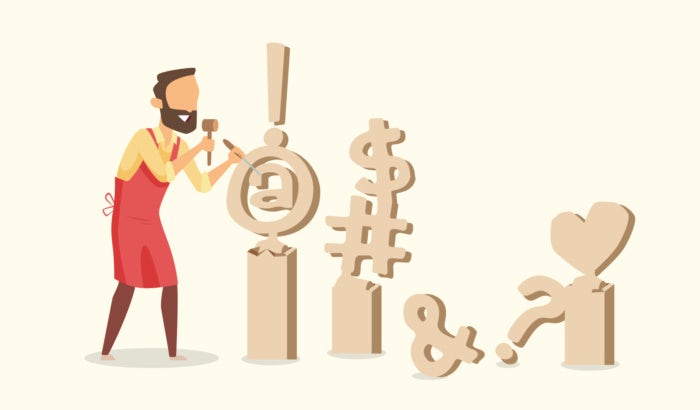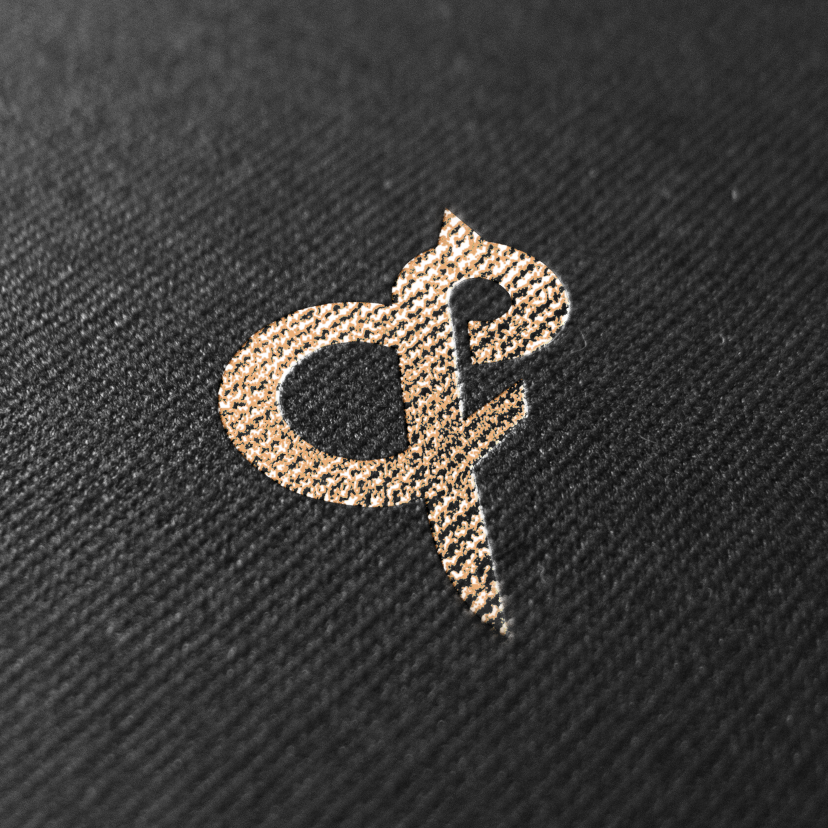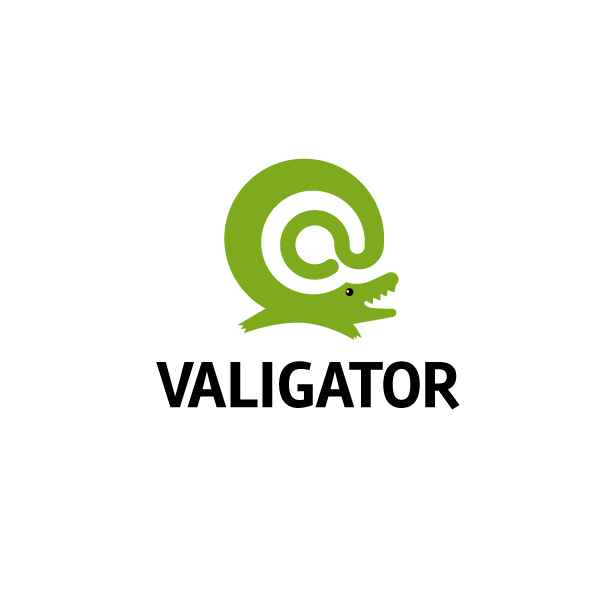
这7个符号你每天都用,但不一定知道它们的起源~
我们每天使用数千个符号。当我们找不到描述我们感受的词语时,我们用它们来传达信息和表达情感。
在设计领域,符号是图形元素的组合,可用于表示品牌的身份,传达其故事并影响消费者的感知方式。
但是,有没有想过每天看到的图形符号背后的起源?
在本文中,我们将探讨七个最广泛使用的图形符号的历史。了解符号的真正含义可以帮助您在自己的工作或公司的品牌中更具战略性地使用它。
1.&符号
设计师们总是无法满获得足够的&符号(&)。
对于设计师来说,这个符号是冒险的邀请,是表达创造力和四处玩耍的机会。Tobias Frere-Jones在一篇关于快速公司的文章中指出了这一点:
"&是一种恐龙。它本该在很久以前就灭绝了,但还是存活了下来。从视觉上看,它是孤独的……通常,通过设置先例和提供上下文,字母有助于形成彼此,但是这些字母并没有得到任何支持。“这使得画图变得困难,但同时也为实验和风险打开了一个异常大的窗口。”
由古罗马人创造的安培人首次出现在庞贝伊的墙上。它一开始是拉丁词et的表示,意思是“和”。
当孩子们说英文字母时,他们在字母本身可以作为一个词来使用(比如a和i)之前加上了本身---一个拉丁短语,意译为“本身”。这看起来像是“一个本身”,“i本身”等等。
最终,符号会出现在字母表的末尾。所以他们发音为“……x,y,z,和本身”,为了发音更快而变形为“……x,y,z,Amperand”。
由nnorth创作的Oats&Ivy徽标中带有创意设计的&符号
2.@符号
早在1971年,美国计算机程序员Ray Tomlinson(称为电子邮件的发明者)发送了第一封电子邮件,用无处不在的符号(@)表示收件人的位置。
今天,会计和编程专家最常使用at符号,但创意设计师就在他们后面。
@符号的起源有三个主要理论:
3.它是“each at”的缩写,首次记载于1536年的西班牙。佛罗伦萨商人Francesco Lapi将塞维利亚的一封信寄给罗马,用@符号表示一个单位的葡萄酒。“在那里,一杯三十分之一的葡萄酒,价值70或80个硬币,” 他写道,用@代表双耳瓶。
由于其独特的形状,@有许多昵称:
Strudel(以色列),猴子尾巴(丹麦),小鸭子(希腊),狗(俄罗斯),蜗牛(意大利),睡猫(芬兰),蠕虫(匈牙利),腌鲱鱼(捷克共和国),老鼠(中国) 等。
据意大利人说,这就是at符号变成蜗牛的方式。通过Jesper Aggergaard。
3.美元符号
您可能听说过美元符号($)是由字母“U”和“S”的字母组成的,就像“美国”一样。
其实不是这样的。
$符号来自“peso” 又名 “ps” 的缩写,最初发生在1770年代,当时英美人与西班牙人有贸易关系。“美元”这个名字来自旧波希米亚货币 - 塔勒。
在设计中,美元符号可以代表国家身份。
4.感叹号
感叹号(!)来自拉丁语“io”,意思是“欢呼”,这是表达喜悦和奇迹的经典方式。为了在纸上分享强烈的情感并节省写作时间,字母“i”写在“o”之上。
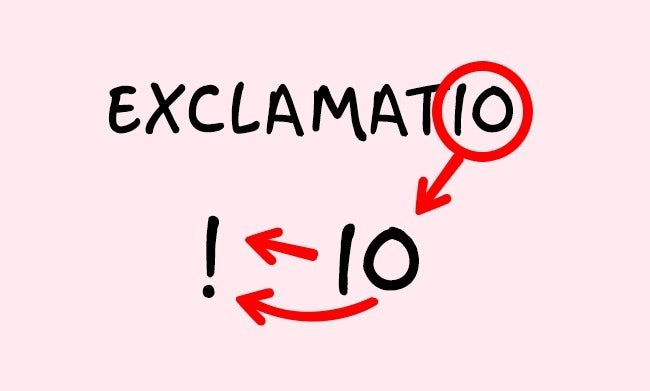
这就是感叹号的来源。通过Letssbuzz。
许多设计师发现这些符号具有多样性。广告牌,平面广告,商业广告,电影海报和网站中都可以见到它的身影。甚至谷歌在1999年的徽标中也有一个惊叹号!
5.#符号
“#”的起源与军队成员每三年服务收到的条纹相关联。它们被称为“hash标记”,可以在军用夹克上找到。
在20世纪80年代,#符号开始被称为“hash”,2007年,前谷歌开发人员Chris Messina使用Twitter建议人们开始使用#topic在同一主题上对推文或其他社交媒体帖子进行分组。在公众抱怨之后,这个符号开始被广泛使用起来。
然后就像电话键盘上的“pound”一样。在这里,拉丁语再次成为事物的根源。Pound是拉丁语中“libra pondo” 又名 “磅重” 的缩写。在写作时,当字母“l”和“p”交叉时,它可以提醒#符号之一。
什么是“octothorpe”?这一次,词源可以追溯到14世纪的“古挪威语”。在古挪威语中,“thorpe”翻译为“field”或“farm”。添加“octo”或“eight”,你就有“eight fields”或“octothorpe”。
今天,标签被广泛用于视频,对话,社交运动和设计中。
Artmin的黑客大会的Cult / Hacker标志
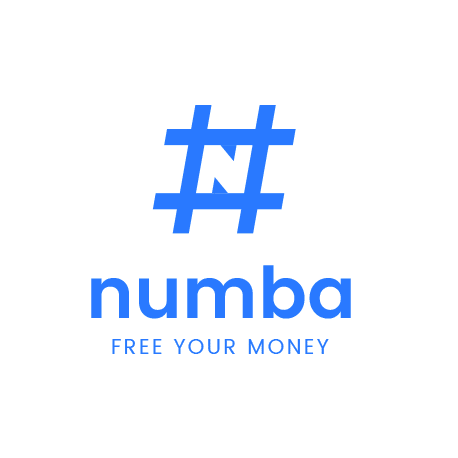
Teo Decu的聊天和汇款应用智能符号
6.无穷大符号
1655年,英国数学家约翰·沃利斯首次提出,无穷大符号被广泛用于物理学,计算机科学和代数中,通常代表潜在的无穷大,而不是实际上无限的数量。
但是如果你深入挖掘一下,你会发现这个符号具有古老的根源和深刻的意义。在印度和西藏,无限代表着二元论和完美,是对立势力与男女统一之间的平衡。在8世纪,无限符号成为圣博尼法斯十字架的一部分,有助于在整个法兰克帝国(今天的西欧)推广基督教。
但是“无限”这个最古老的含义出现在埃及的Ouroboros上,这是一条蛇吃着它自己的尾巴 - 一种不那么微妙的死亡和重生循环的代表。
然而有些人坚持认为这个符号也可能来源于希腊字母Omega:Ω。
平面设计师挖掘这个古老的象征,用它来传达永恒与和谐的思想。
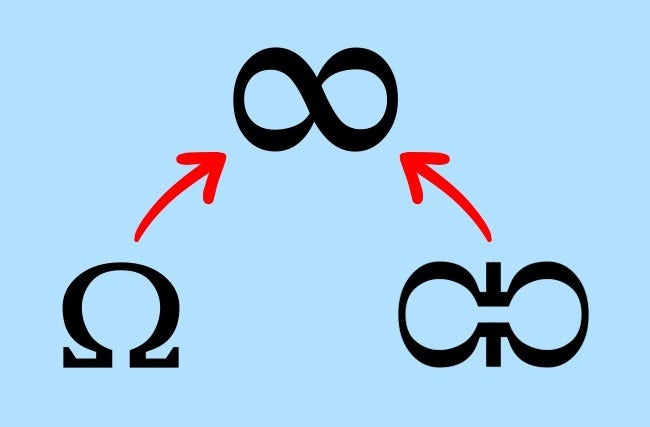
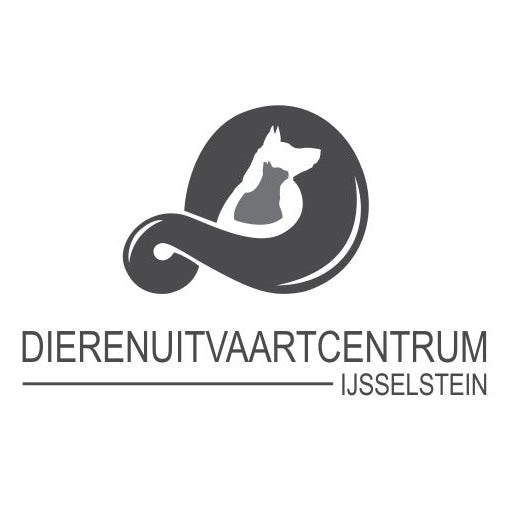
由maneka创造性地使用无限标志标志
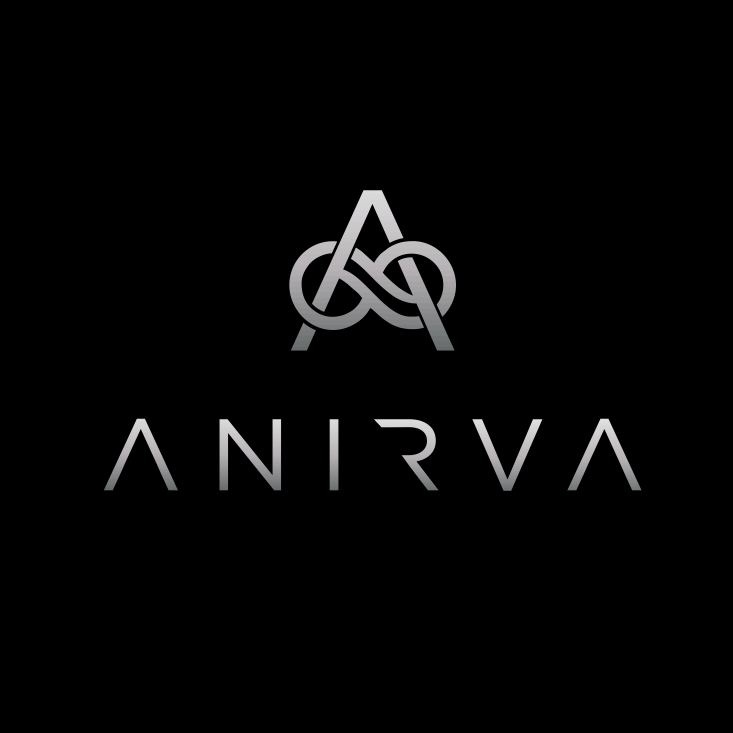
优雅的标志与goreta无限标志
7.心脏符号
心脏是图形设计中使用最广泛,有些人可能会说过度使用的符号之一。在设计师Milton Glaser设计之后,这个现在无处不在的象征得到了新的生命。
- 是的,他是免费做的
- 他的I Heart NY品牌在20世纪70年代纽约市售出。
今天,这是代表爱情最明显的象征。善良,团结,感情和忠诚(以及其他)。
心脏起源背后有许多理论。据说代表:
无论起源是什么,我们大多数人都将这个符号与爱联系起来。我们使用它来标记社交媒体上最喜欢的帖子和照片,我们将它发送给我们最亲爱的人。它是千言万语的普遍象征,所以它似乎永远不会成为陈词滥调。
符号,现在和永远